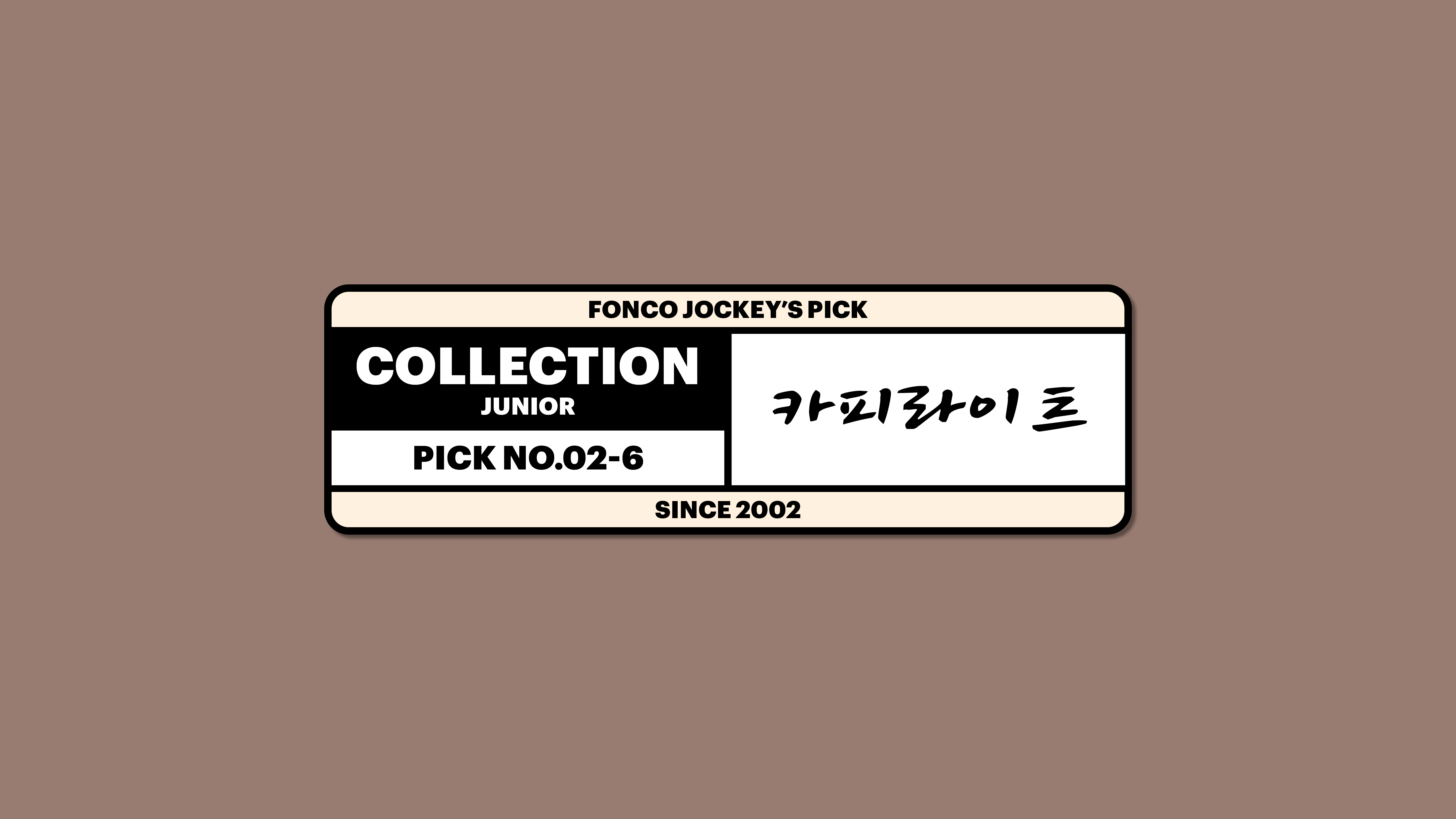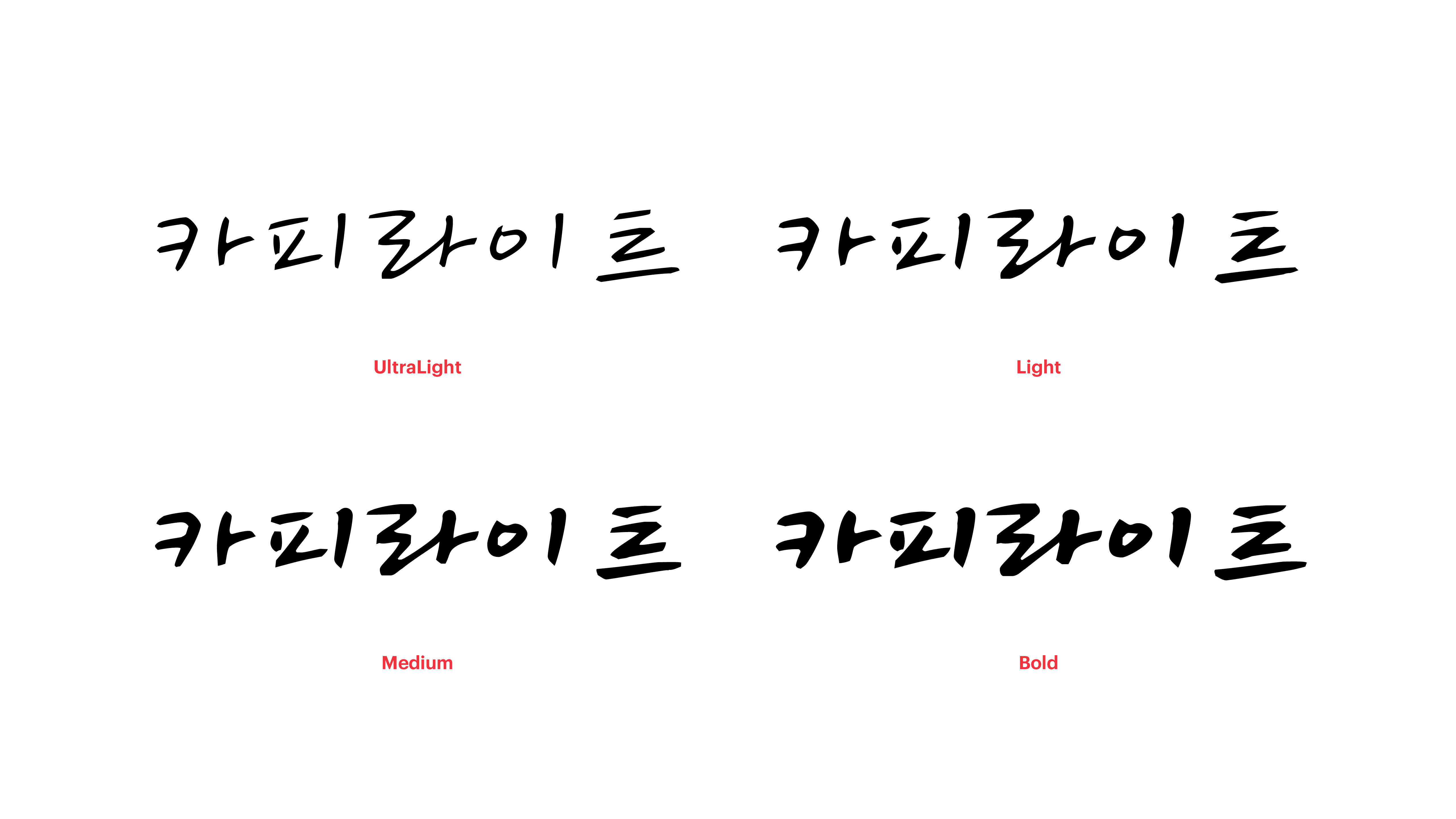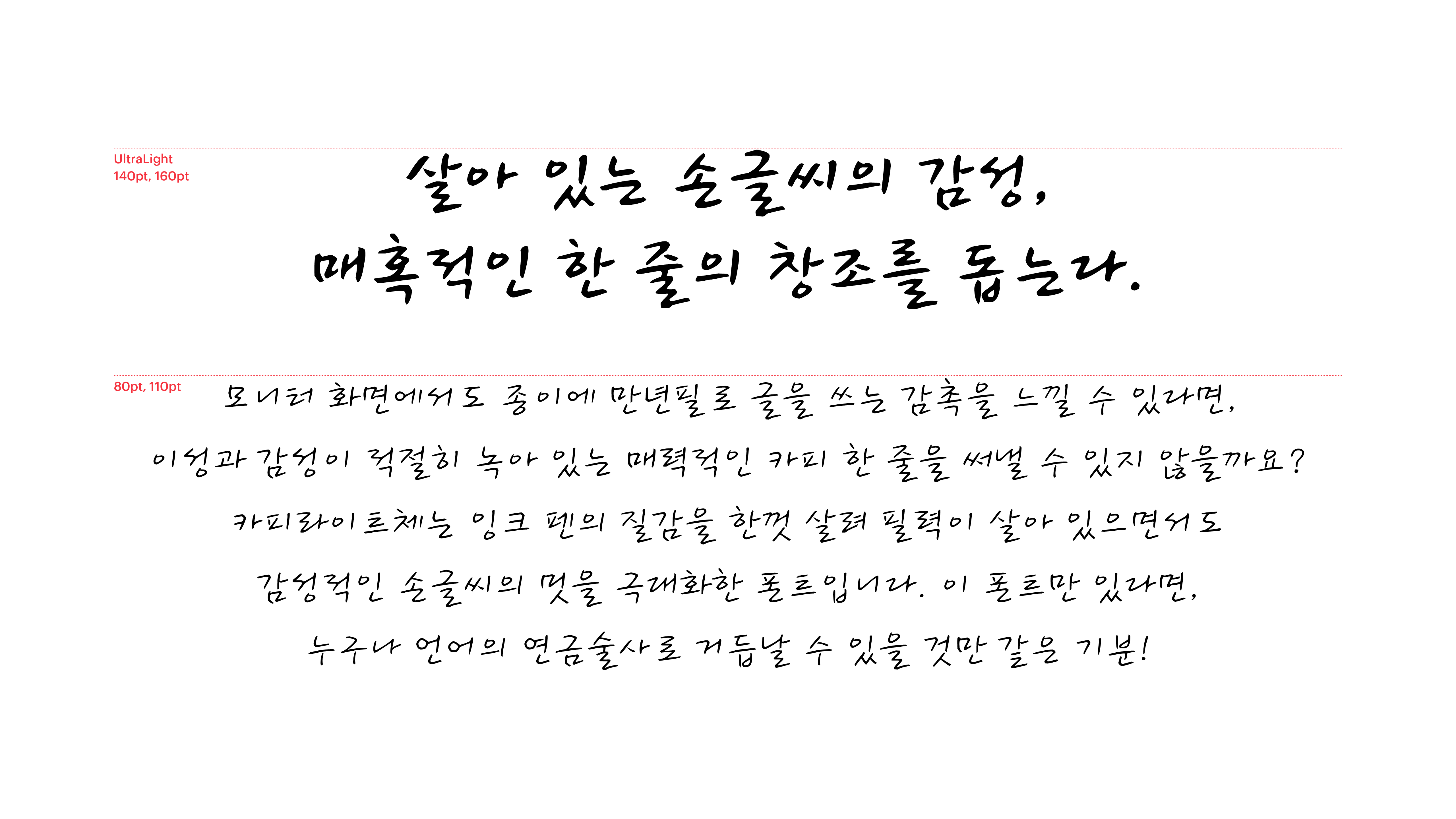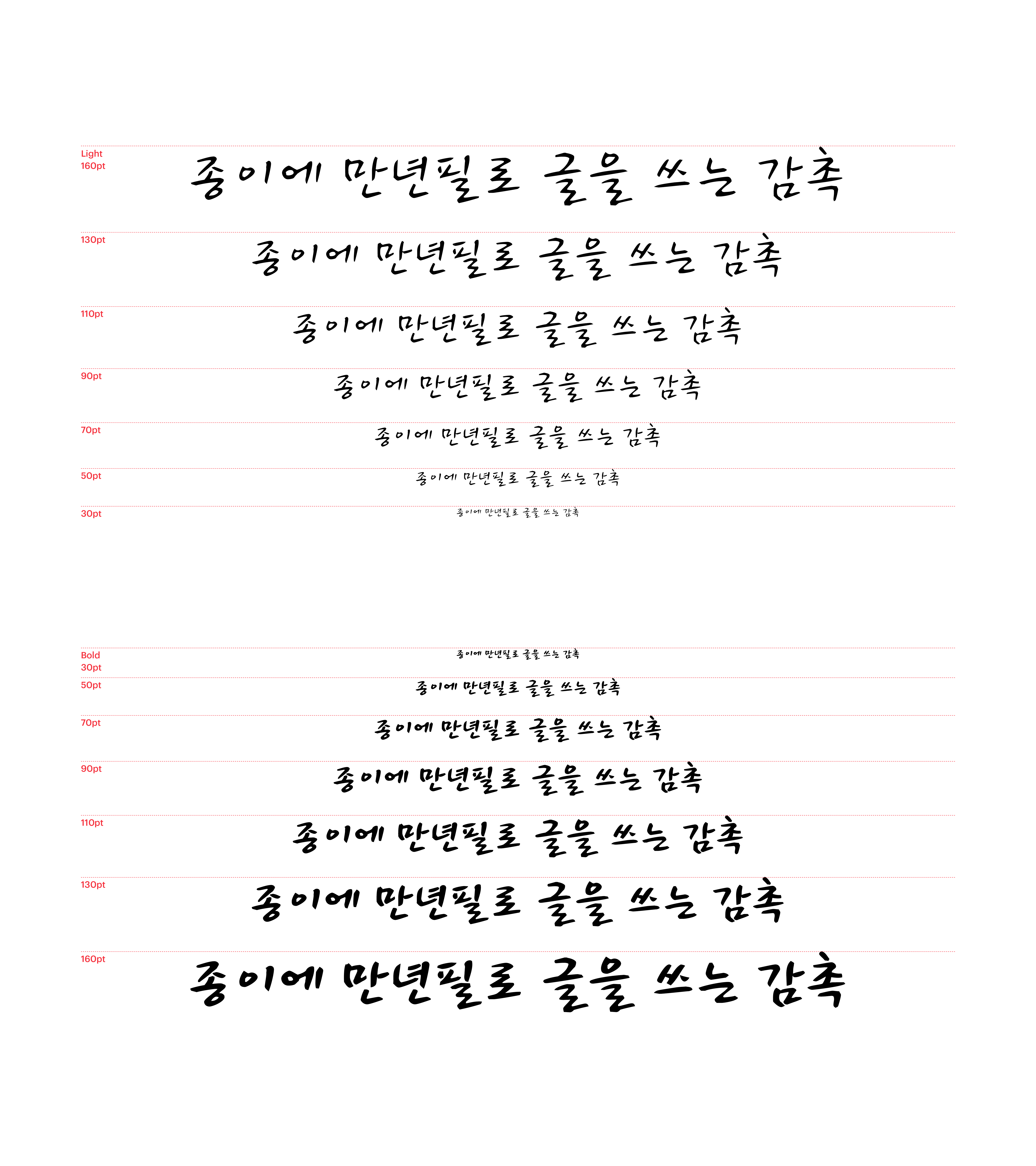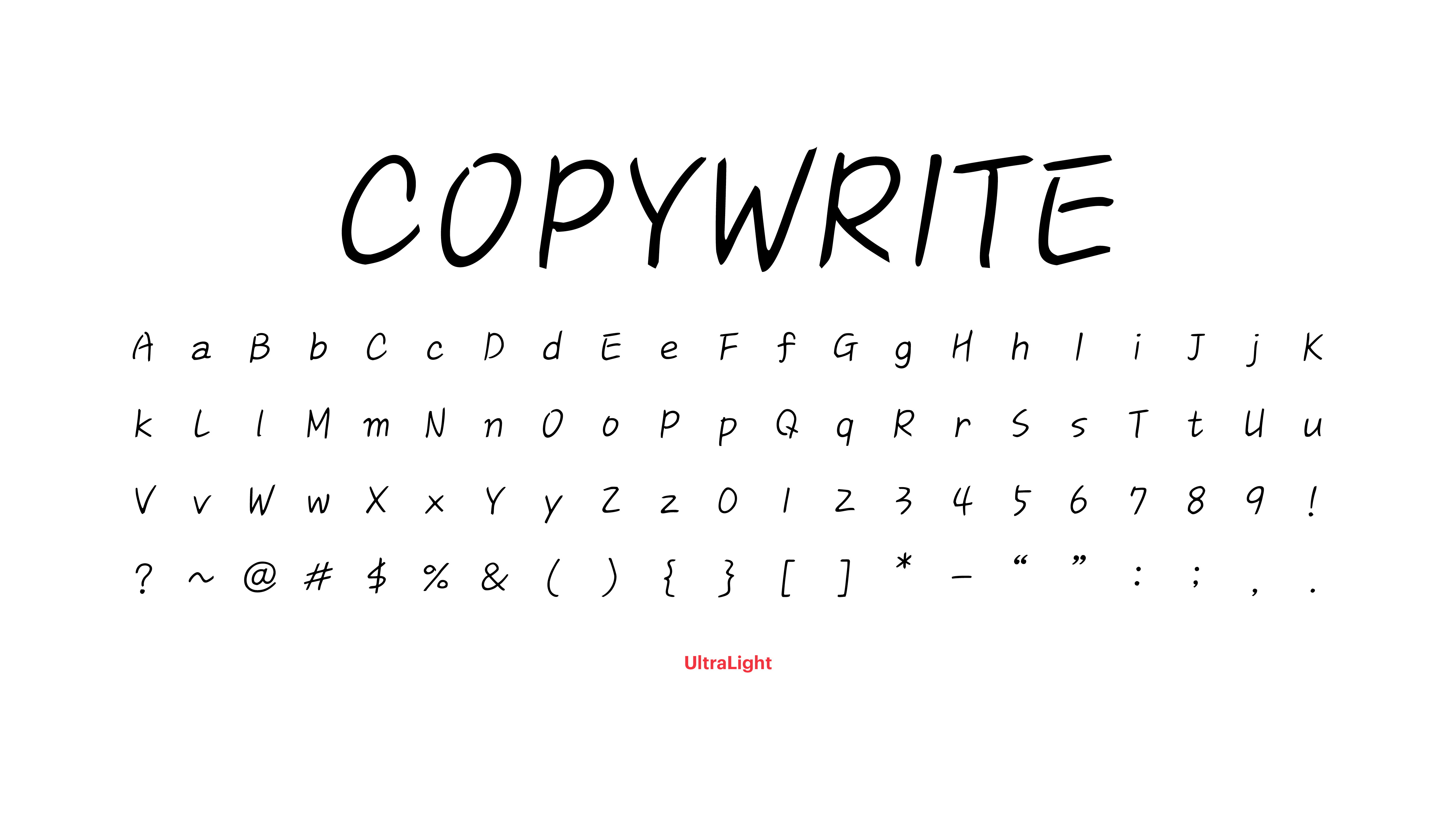
모니터 화면에서도 종이에 만년필로 글을 쓰는 감촉을 느낄 수 있다면, 이성과 감성이 적절히 녹아 있는 매력적인 카피 한 줄을 써낼 수 있지 않을까요? 카피라이트체는 잉크 펜의 질감을 한껏 살려 필력이 살아 있으면서도 감성적인 손글씨의 멋을 극대화한 폰트입니다. 이 폰트만 있다면, 누구나 언어의 연금술사로 거듭날 수 있을 것만 같은 기분!
Yoon 카피라이트